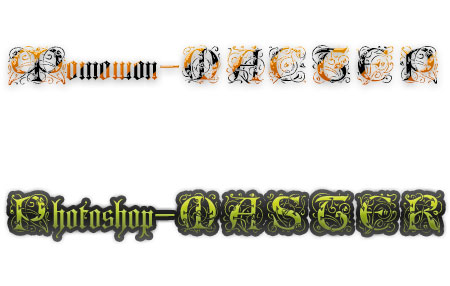
Очень красивый шрифт!!!
Очень красивый, спасибо большое!
Классный шрифт *_*
Прелесть!!!! УРА!!!
Дааа.... уж...
Гламурненько :)
спасибо ! тащусь от этого шрифта !:D
Красивый. Я как раз такой искала.
ОЧЕНЬ ОРИГИНАЛЬНО!
Действительно, очень симпатичный.
Ну очень красиво!
Симпатичный и заливка подходящая !!!
Блеск!!!!
классный шрифт, спасибо!
Спасибо! Какой тяжёлый!
Особенно зелёный